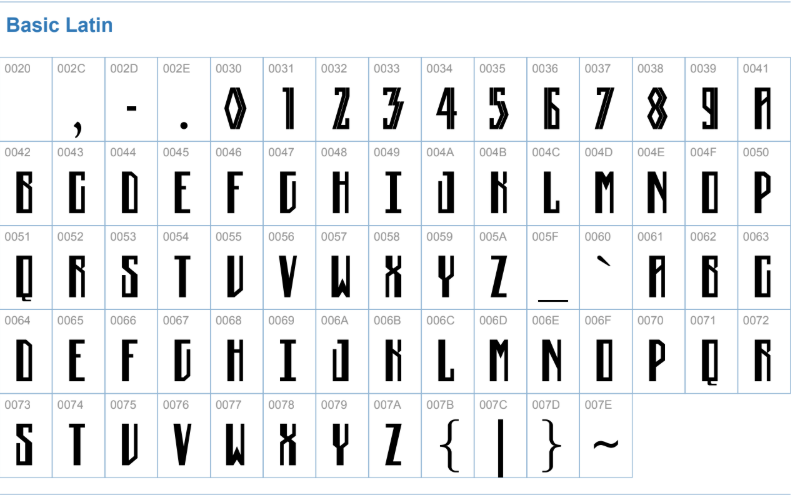
A caminho de mais uma Copa do Mundo, a Seleção Uruguaia renova sua identidade visual com uma tipografia exclusiva para 2026. O novo conjunto de caracteres chega para conectar tradição e performance, traduzindo a garra charrua em cada nome estampado no manto celeste.
Designers e torcedores já estão de olho na fonte oficial que vai vestir os uniformes da Celeste. Mais do que um simples alfabeto, a tipografia da temporada funciona como extensão da alma do time — e agora você pode conhecer (e baixar) cada detalhe desse lançamento.
Estilo visual da tipografia
Os números têm construção geométrica, levemente condensada, com cantos vivos e acabamento sólido. As serifas aparecem de forma sutil, trazendo um toque clássico que dialoga com a história do futebol uruguaio, mas sem perder a pegada moderna que o jogo atual exige.
As letras priorizam legibilidade total em campo e nas transmissões de TV, com hastes firmes, espaçamento generoso e desenho que não some nas costas do uniforme — mesmo nas câmeras mais distantes.
Aplicação no uniforme
Home (titular): nomes e números em branco contrastando com o azul tradicional, mantendo a elegância característica.
Away (reserva): aplicação em azul escuro sobre base branca, com excelente leitura à distância.
Third (terceira): detalhes em preto fosco sobre o tom celeste alternativo, reforçando o visual arrojado da campanha 2026.